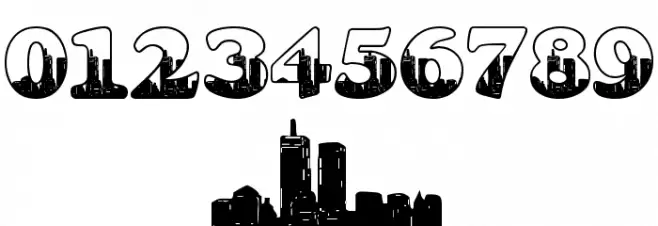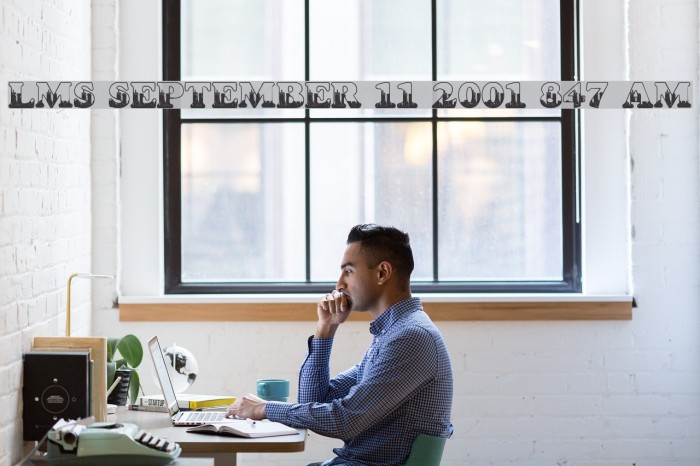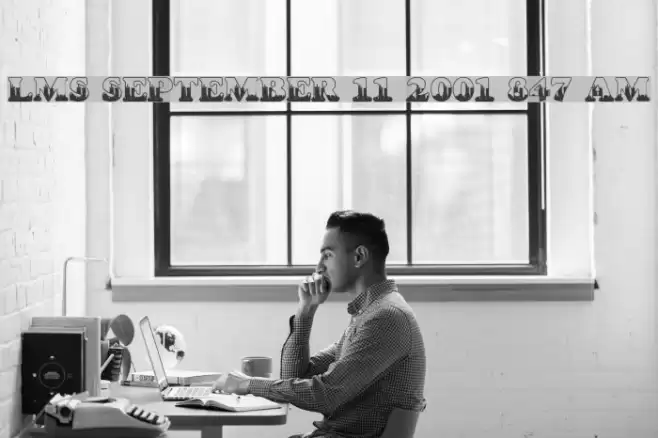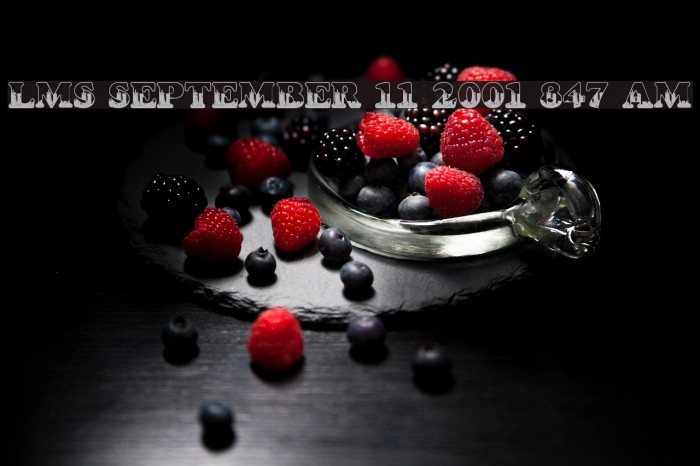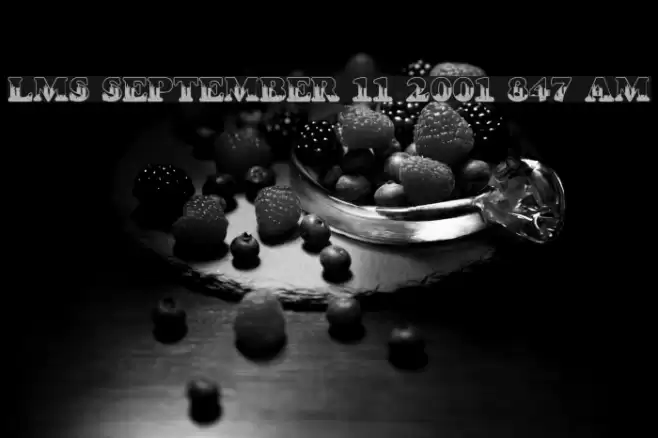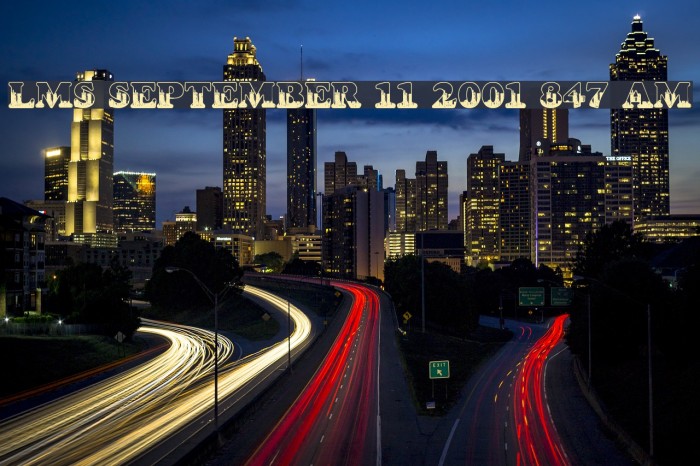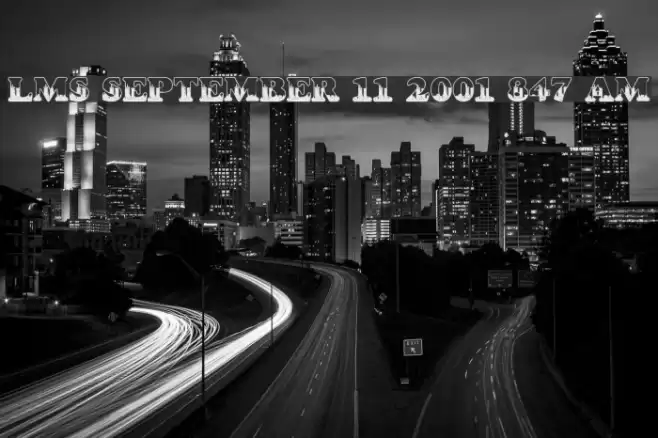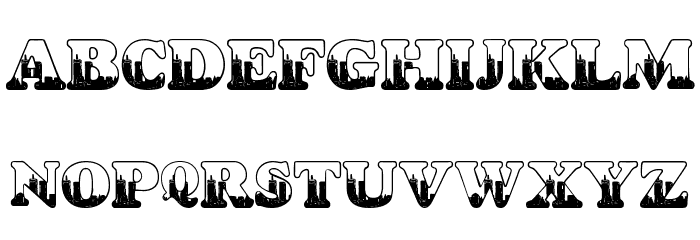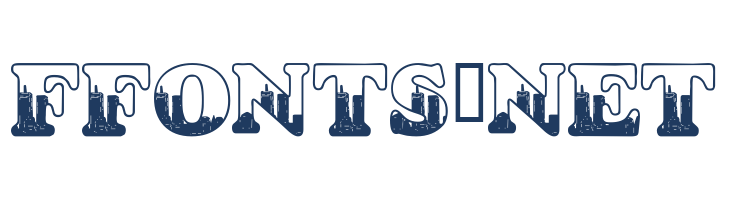
LMS September 11 2001 8:47 AM Font
| おすすめプロジェクト | Ideal for posters, event invitations, themed branding, or any project requiring a dramatic urban aesthetic. |